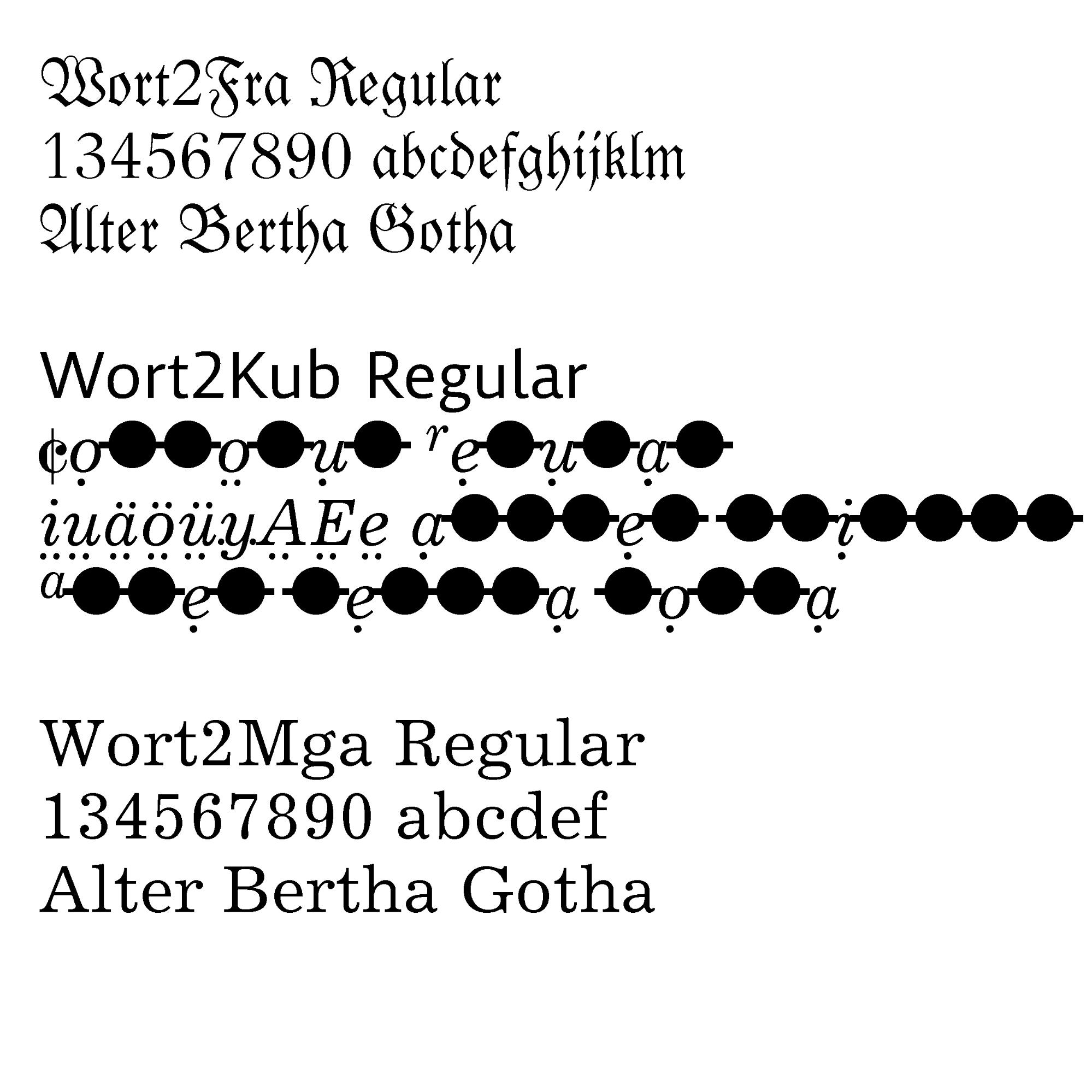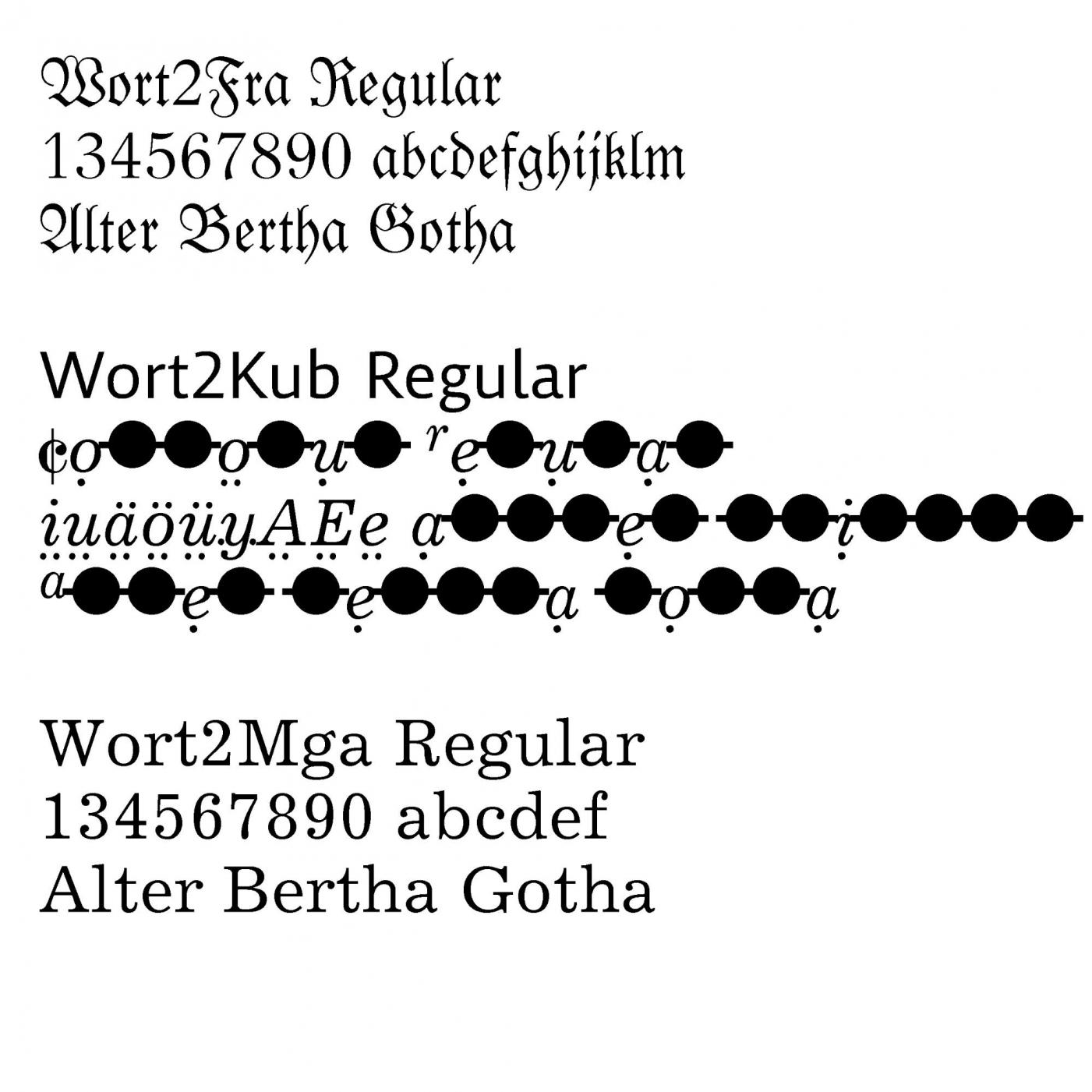
Kennt wer eine Schrift namens Wort2?
Ein Kunde verfügt über eine »alte«, lange nicht verwendete TrueType-Schrift. 3 Fonts liegen vor:
Wort2Fra Regular
Wort2KuB Regular
Wort2MgA Regular
Da sich beim Kunden die Frage nach den Nutzungsrechten stellt und er auch gerne eine aktuelle OTF-Version der Schrift hätte: Kennt jemand  diese Schrift (Fra = Fraktur, Kub = Sonderzeichen?, Mga = Serif / siehe Schriftmuster)? Gibt’s/gab’s einen Hersteller dafür?
Scheint ja wohl eine wild modifizierte Schrift zu sein:
Wort2Fra = Luthersche Fraktur, Wort2Mga = Excelsior Roman oder Medium, Wort2Kub = Excelsior Italic (mit individuellen Sonderzeichen/Anpassungen).
Liege ich da richtig? Oder weiß wer mehr?
Danke, Bertel, danke, Ralf! Ja, ich hab’ jetzt in den Fontdaten noch ein paar Hinweise auf Blackletter 581 (ist wohl die Bitream’sche Version der Lutherschen Fraktur?) und auf die Excelsior gefunden. Die »merkwürdige« Wort2Kub scheint eine Modifikation der Excelsior Italic zu sein – allerdings mit unvollständigen Glyphen – nur ein paar überarbeitete Selbstlaute + Ligaturen + Sonderzeichen, die auf Notensatz hindeuten.